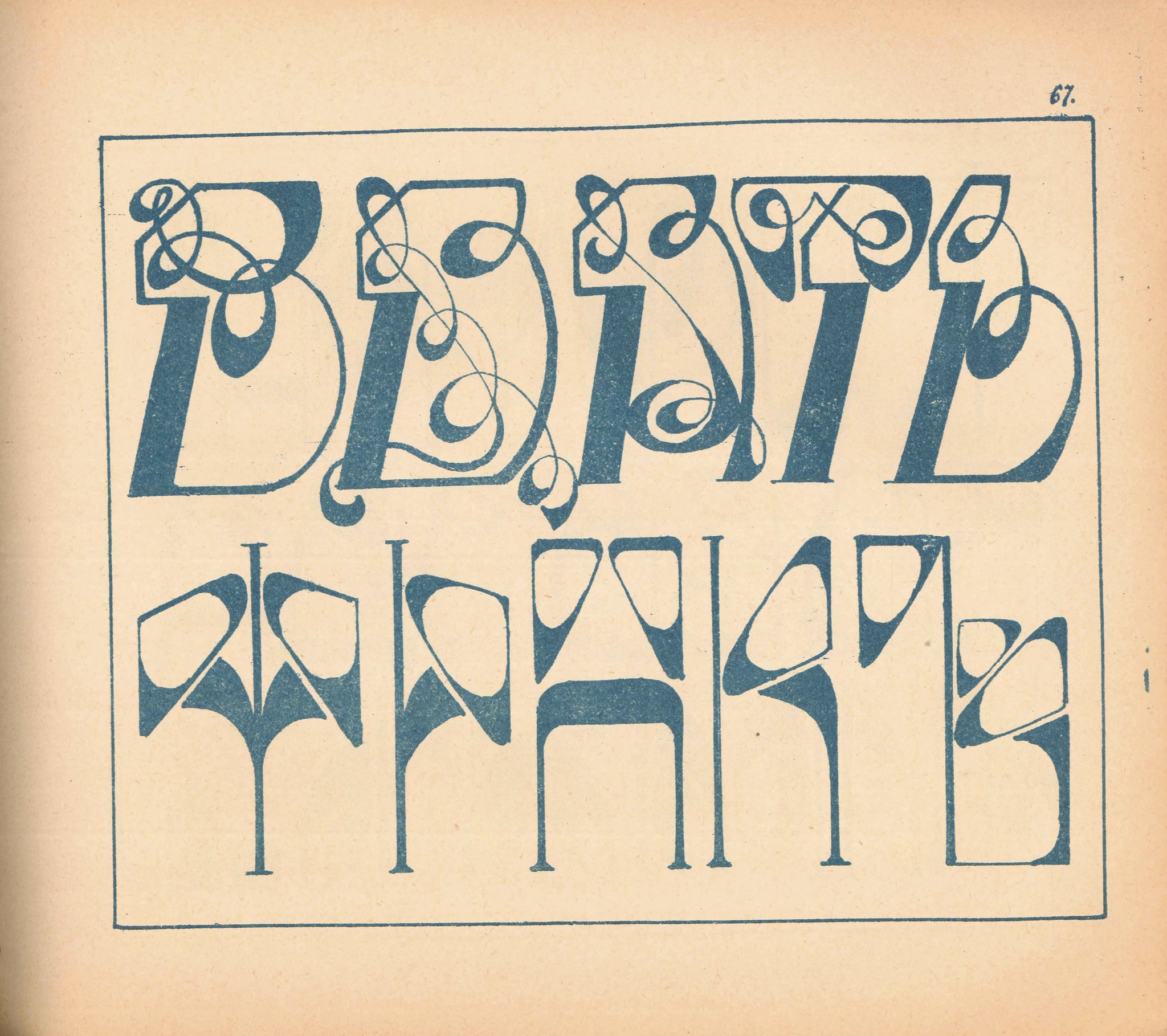
Наборный и рисованный шрифты существуют параллельно, и использование каждого из них вовсе не означает невозможность применения другого. Различия между этими видами шрифтов велики, но не настолько, чтобы не возникала возможность их влияния друг на друга.
Принципиальными свойствами наборного шрифта являются стандартность, универсальность и надиндивидуальность. Наборный алфавит сконструирован из стандартных взаимозаменяемых элементов (стоек, штрихов и т. д.), начертание которых стабильно и закономерно. Каждый наборный шрифт имеет присущую всем его знакам и литерам ширину и высоту (вернее, соотношение высоты и ширины). Эта закономерность обеспечивает гармоничность шрифта и его художественную целостность. Кроме того, каждый наборный шрифт универсален. Это значит, что он может быть использован в любых целях, независимо от того, для чего его изобрел автор. Универсальность шрифтов отражается и в разнообразии способов их воспроизведения: наборный шрифт может быть не только напечатан, но и скопирован, отштампован или отлит из различных материалов, вырезан и расклеен.
Рисованный (рукописный, гравированный и т. д.) шрифт имеет полностью противоположные качества. Он создается ради конкретного произведения — надписи, а не для изобретения гарнитуры. Искусство рукописного шрифта неотделимо от живописи и графики, к которым неприменимо понятие о расчленении процесса на этапы проектирования стандартных деталей и последующей компоновки из них каких– либо конструкций. Знаки, составляющие рукописную надпись, не существуют отдельно друг от друга. Вся композиция воспринимается, как единое произведение, ее нельзя разложить на составные элементы, подобно тому, как наборный шрифт разделяется на литеры. Рисованную надпись невозможно стандартизировать, она всегда индивидуальна.
Виды шрифта (наборный и рисованный) влияют друг на друга. Так, рисованный шрифт может быть использован в качестве основы при разработке наборной гарнитуры. Нередко предпринимаются и попытки внести строгость и усредненность наборного шрифта в рукописные надписи.
ОСНОВНЫЕ
ТИПЫ ШРИФТОВ
В ЗАВИСИМОСТИ
ОТ ТЕХНИКИ
ИХ ИСПОЛНЕНИЯ.
ИСТОРИОГРАФИЯ
ВОПРОСА
В зависимости от техники исполнения или воспроизведения различают
следующие основные типы шрифта.
Рукописный, которым пишут тексты от руки палочкой или пером на
мягком материале (папирусе, пергаменте, бумаге). До возникновения книго-
специальных заведениях (скрипториях, канцеляриях) или непосредственно
отдельными лицами.
Разновидностью способа исполнения рукописногошрифта является каллиграфия (искусство красиво писать), получившая
широкое развитие особенно в период господства стиля барокко в XVII веке.
Гравированный, при помощи которого воспроизводятся надписи на
камне, дереве, металле или другом твердом материале различными
приемами гравирования; надписи эти выполняются или непосредственно на
памятниках, архитектурных сооружениях, табличках, или на гравюрах.
дереве (появились в XV веке одновременно с возникновением книгопечата¬
ния, например, «Библия бедных») или на металле (например, русские
буквари конца XVII века).
Рисованный, при помощи которого выполняются надписи на вазах,
тканях, переплетах, обложках, титульных листах и других элементах
изданий. Гравированные и рисованные шрифты наравне с рукописными
имели широкое применение на различных этапах развития письма (до и
после возникновения и распространения книгопечатания).
Типографский, или наборный, в котором слова или строки текста
составляются вручную из отдельных литер или с помощью тех или иных
машин — строкоотливных, буквоотливных, фотонаборных или наборно-
пишущих.
Понятие «шрифт» как графическую форму определенной системы
письма мы относим ко всем перечисленным типам шрифта, независимо от
того, как они воспроизводятся (пером, резцом, кистью, типографским
набором и т. д.). Термин «почерк»—это чаще всего индивидуальная
особенность письма, в частности, отдельного человека». Поэтому термин
«тип рукописного шрифта» (как родовое понятие) мы употребляем для
обозначения основных типов почерков различных рукописных памятников, а
термин «почерк» (как видовое понятие)—для разновидности этих типов12.
Определенное влияние на рисунок шрифта оказывает техника испол¬
нения. Это особенно заметно в рукописных шрифтах, рисунок которых во
многом зависит от инструмента письма. Так, рукописные шрифты средневе¬
ковья (готические, уставные) выполнялись ширококонечным птичьим пером,
в то время как гуманистическое письмо эпохи Возрождения и русское
гражданское конца XVII —начала XVIII века —заостренным.
Разное решение рисованных надписей также требует использования
различных инструментов письма (кисть, заостренное или ширококонечное
перо) .
контрастен по сравнению со шрифтом, выполненным на металле. В
последнем случае рисунок шрифта более четкий, а засечки приобретают
ВВЕДЕНИЕ
11
форму тонкой черточки. Особенно показательны шрифты А. Дюрера, грави¬
рованные на дереве и металле.
Следует, однако, учесть, что техника исполнения шрифта только в
определенной мере и далеко не всегда (особенно в наборном шрифте)
влияет на его рисунок.
Большую роль играет в графике письма индивидуальная манера
пишущего. Это отмечено С. А. Рейсером: «Специальными опытами доказано
Вот почему, если строка надписи, из надлежащего размера букв, не умещается в данных пределах на чертеже, можно значительно уменьшить размер букв, и только первые буквы слов выделить по размеру, напр.,
Особенную трудность представляют надписи длинные, т. к. тут неправильное расположение отдельных строк может забить даже четкость и красоту шрифта, и этим испортится вид всего чертежа.
Употребим здесь техническое выражение: строки надписи должны располагаться вазой; поясним сказанное: